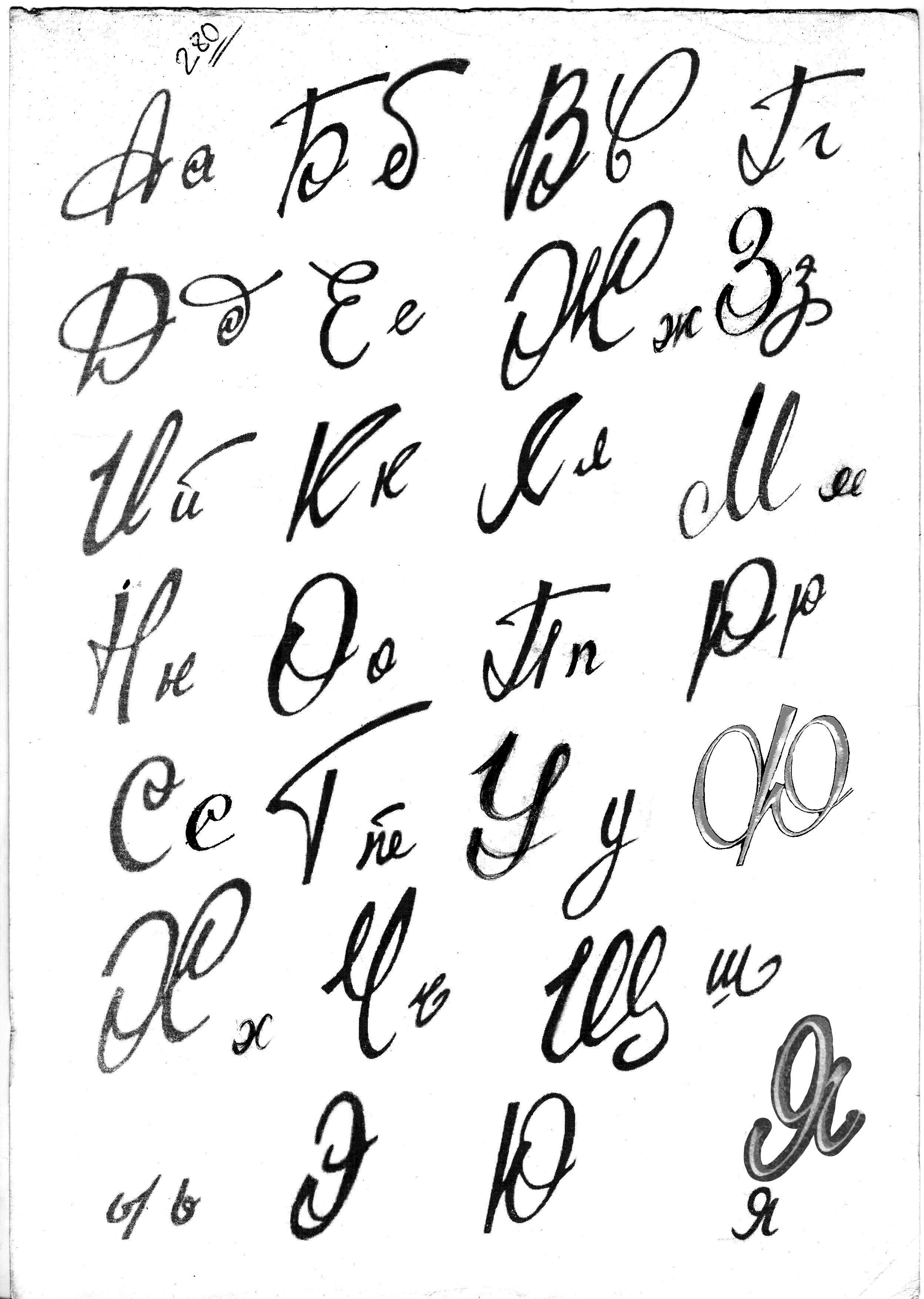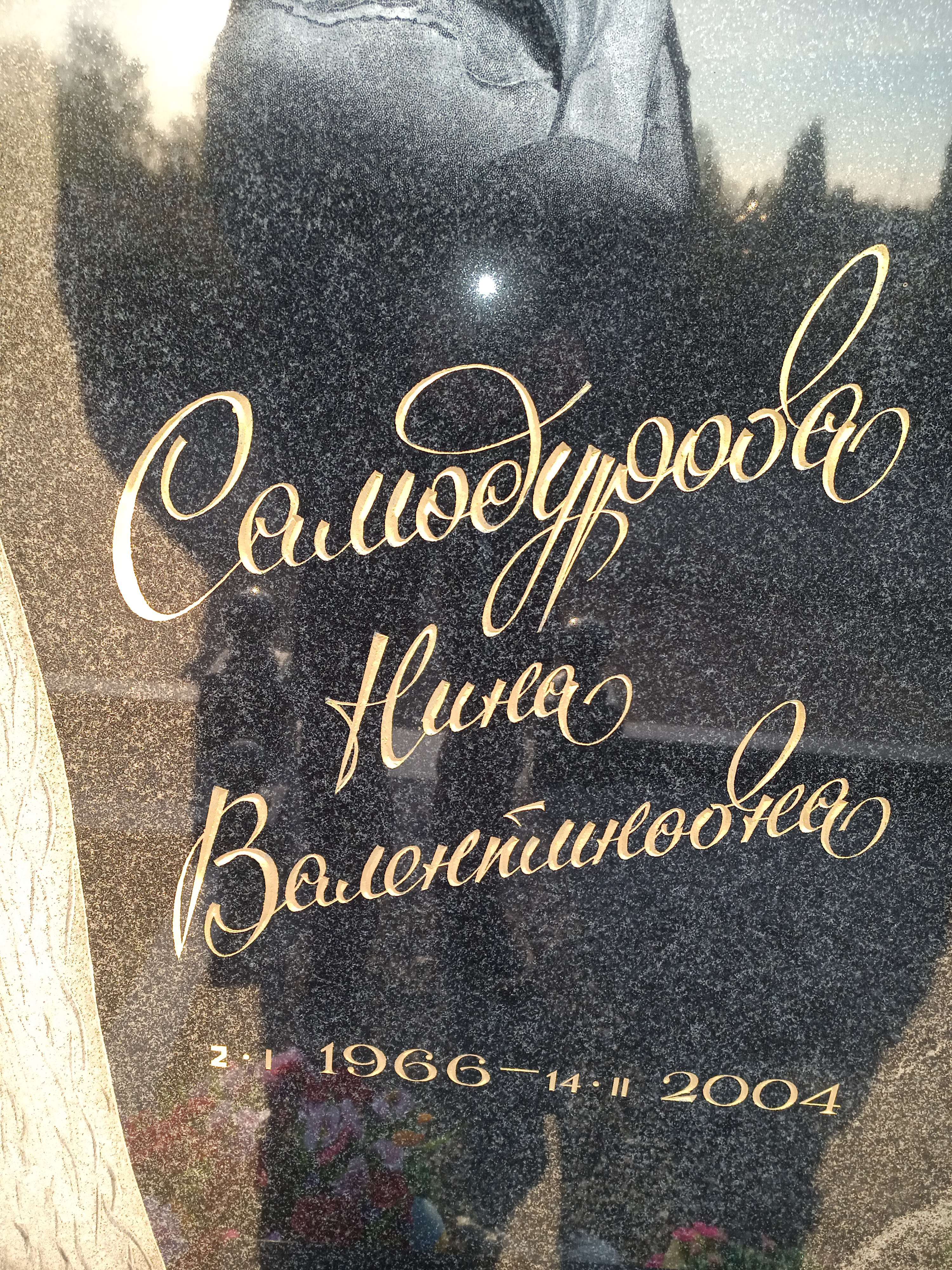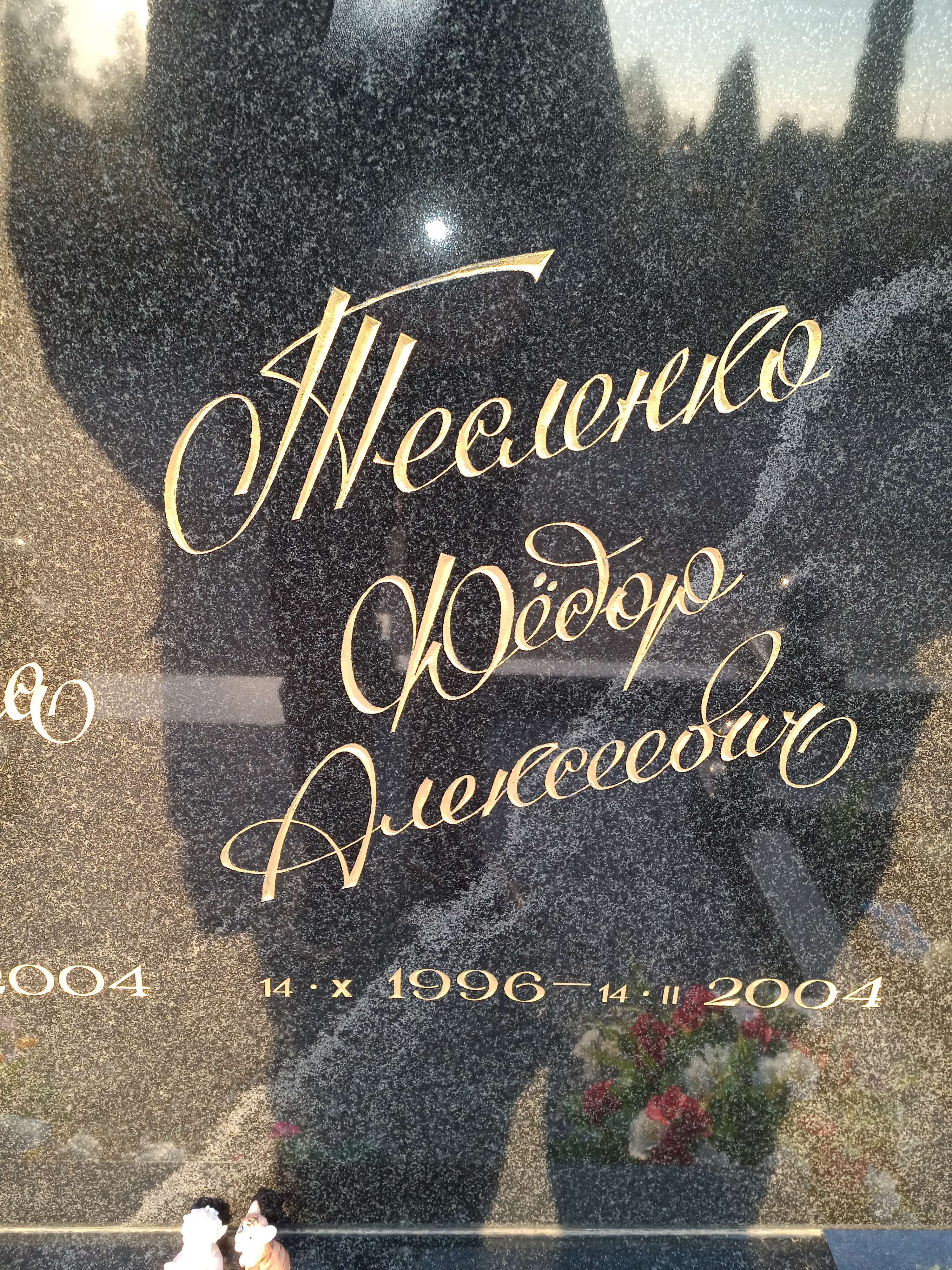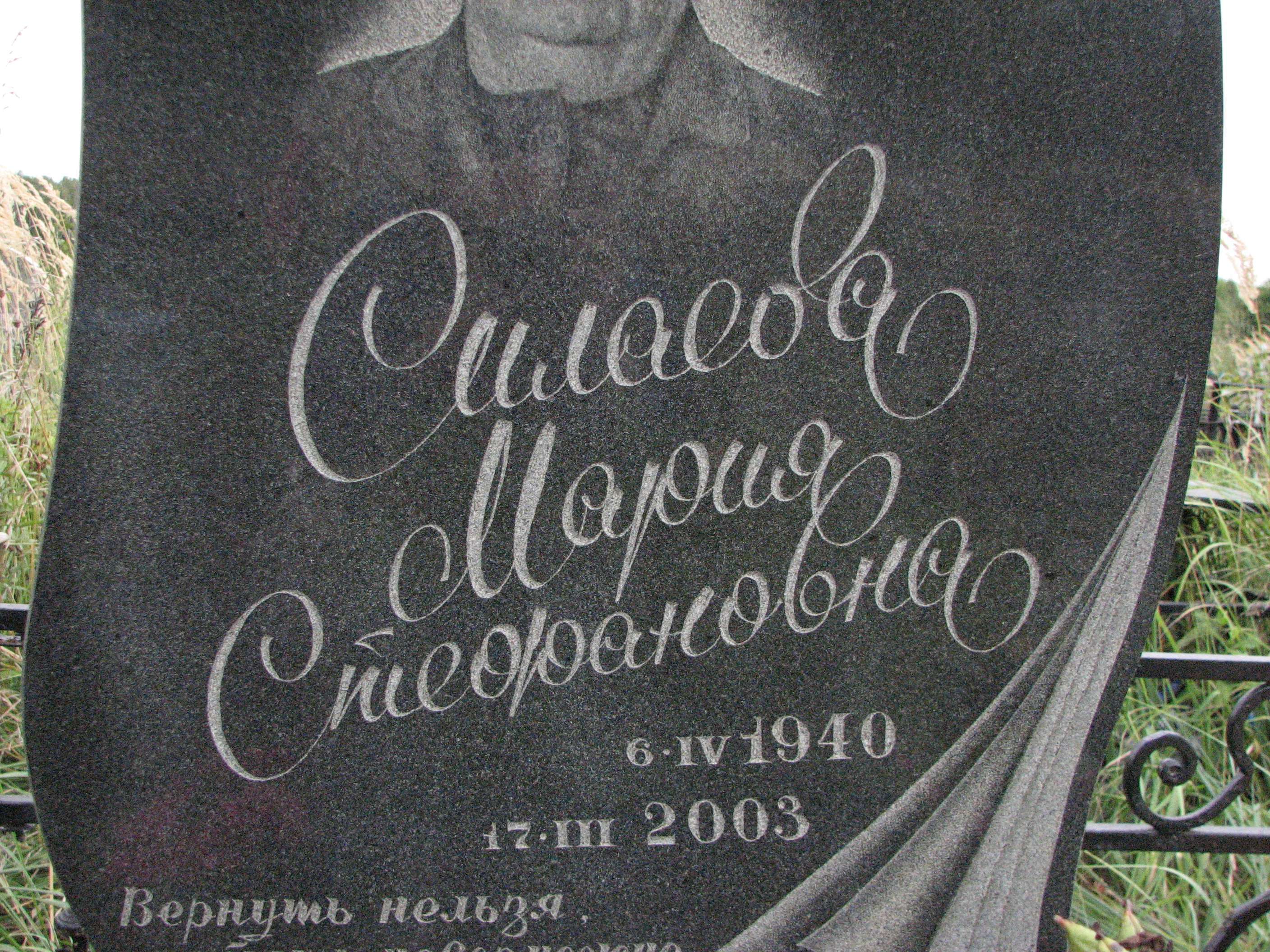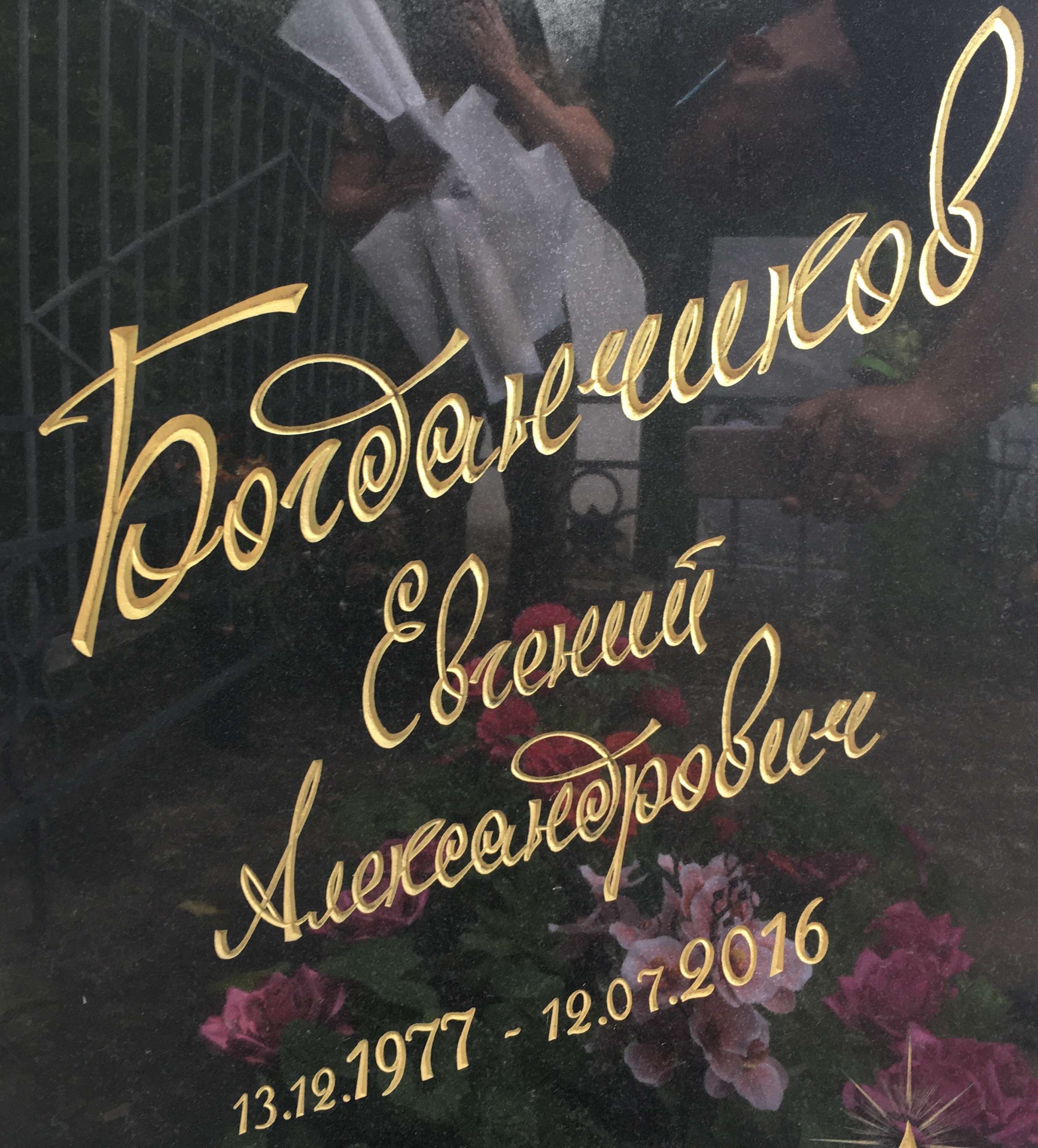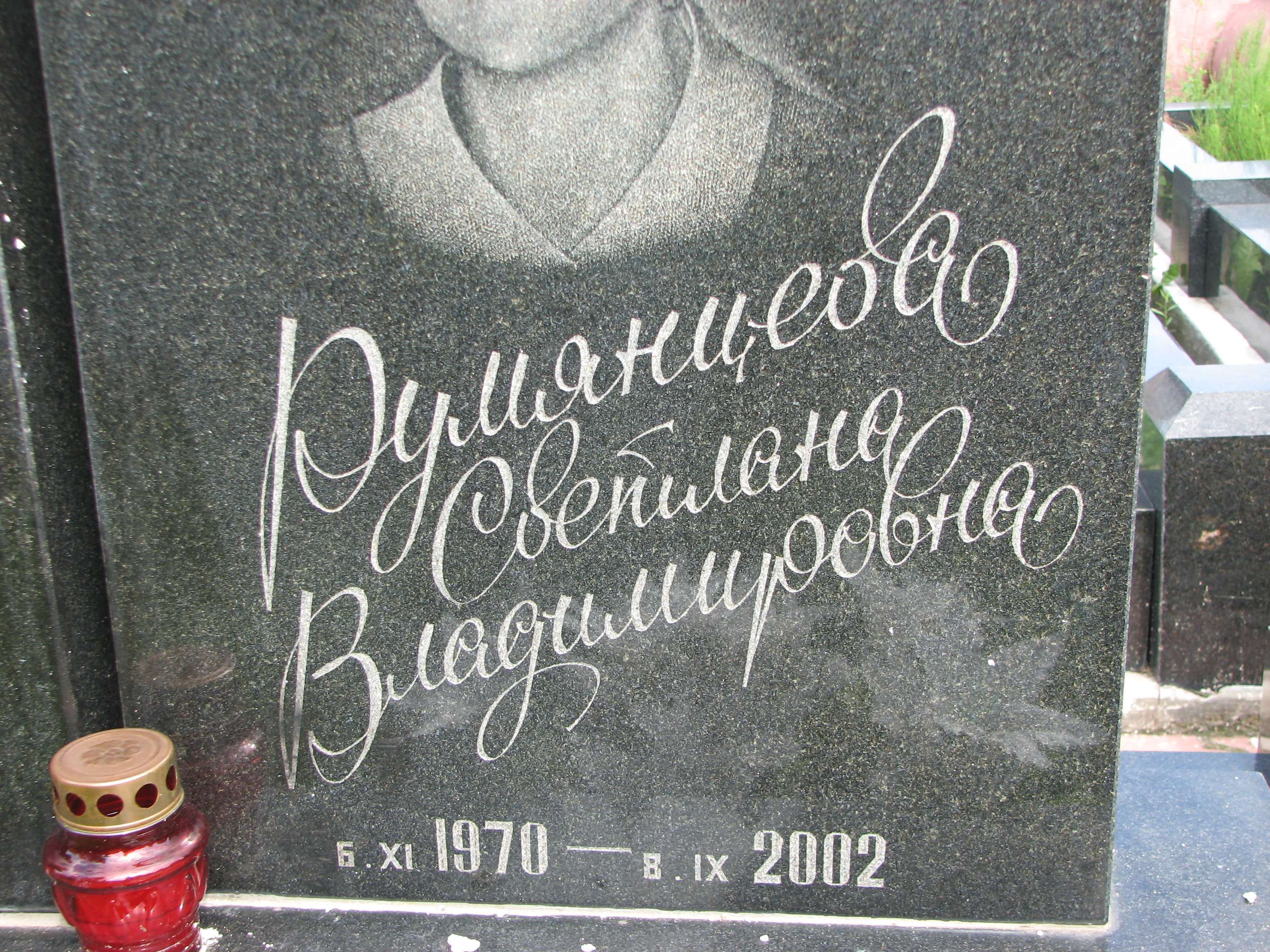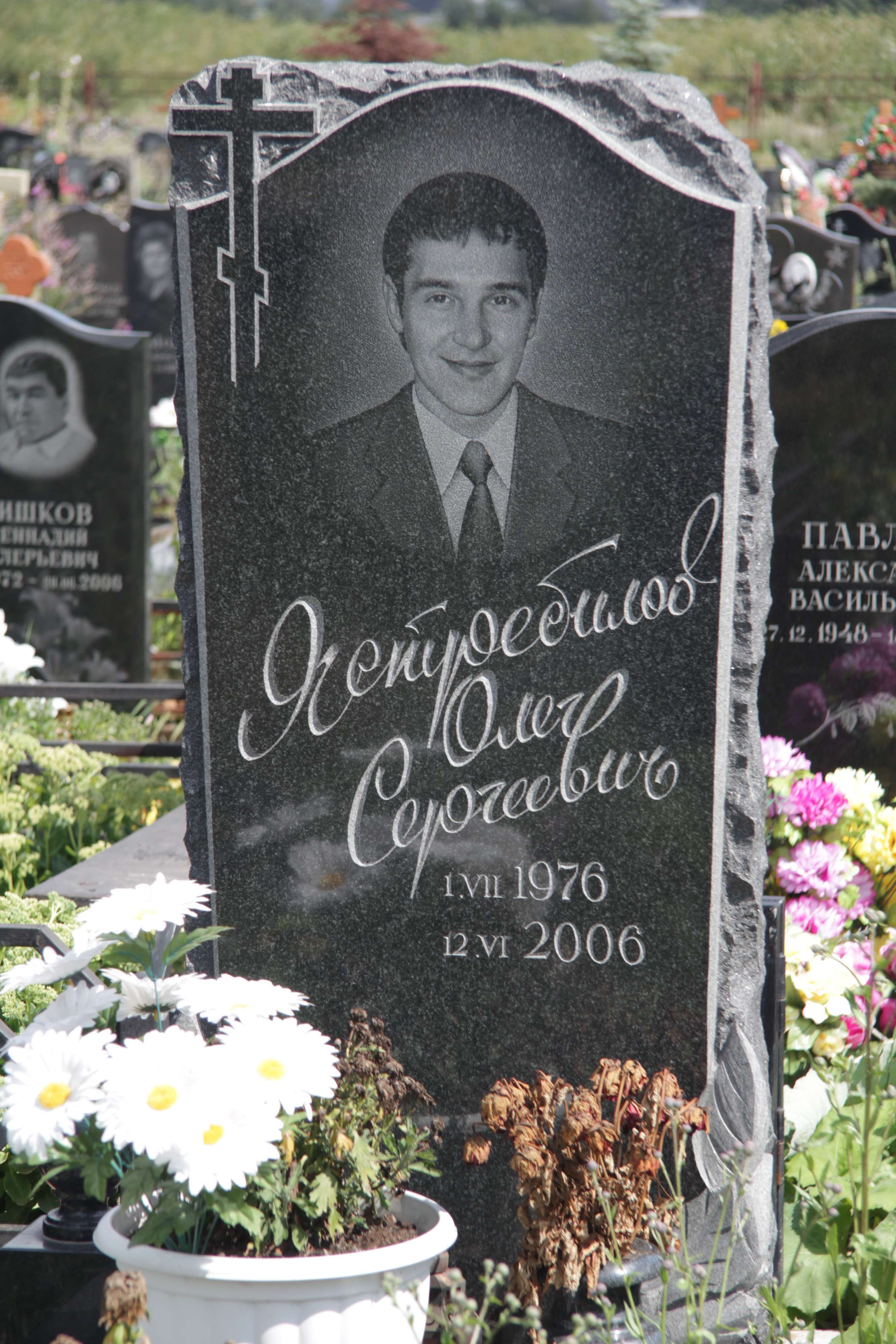
УльянаЛ Опубликовано 16 июня, 2025 помогите найти шрифты ФИО дат и эпитафии.
Connar Опубликовано 16 июня, 2025 20 минут назад, УльянаЛ сказал: ФИО AGBenguiat Cyr Book кроме !К! вообще наверное ручной. кривоват 1
УльянаЛ Опубликовано 16 июня, 2025 @Connar Да не ручник, говорят станком били. спасибо Не не AGBenguiat Cyr Book не идёт там и Л и А другие совсем.
igors Опубликовано 16 июня, 2025 @УльянаЛ типичный ручник все коряво сделано
AndreyV Опубликовано 28 июня, 2025 Добрый день! Помогите пожалуйста найт похожий шрифт.
Romeo Опубликовано 28 июня, 2025 Добрый день. Помогите пжста найти название шрифта. Вроде простой и тут где то видел,а найти не могу
a-revus Опубликовано 28 июня, 2025 (изменено) 3 часа назад, AndreyV сказал: Добрый день! Помогите пожалуйста найт похожий шрифт. добрый день! нашёл похожий шрифт. подойдёт вам такой? могу ещё много найти. Изменено 28 июня, 2025 пользователем a-revus 1
AndreyV Опубликовано 28 июня, 2025 @a-revus Очень похож, как называется данный шрифт?
a-revus Опубликовано 28 июня, 2025 Называется взял в руку карандаш, накидал на камне примерно,, взял в руку скарпель, в другую киянку, настучал похожий. 1
Владимир65765187 Опубликовано 30 июня, 2025 Помогите найти шрифт пожалуйста